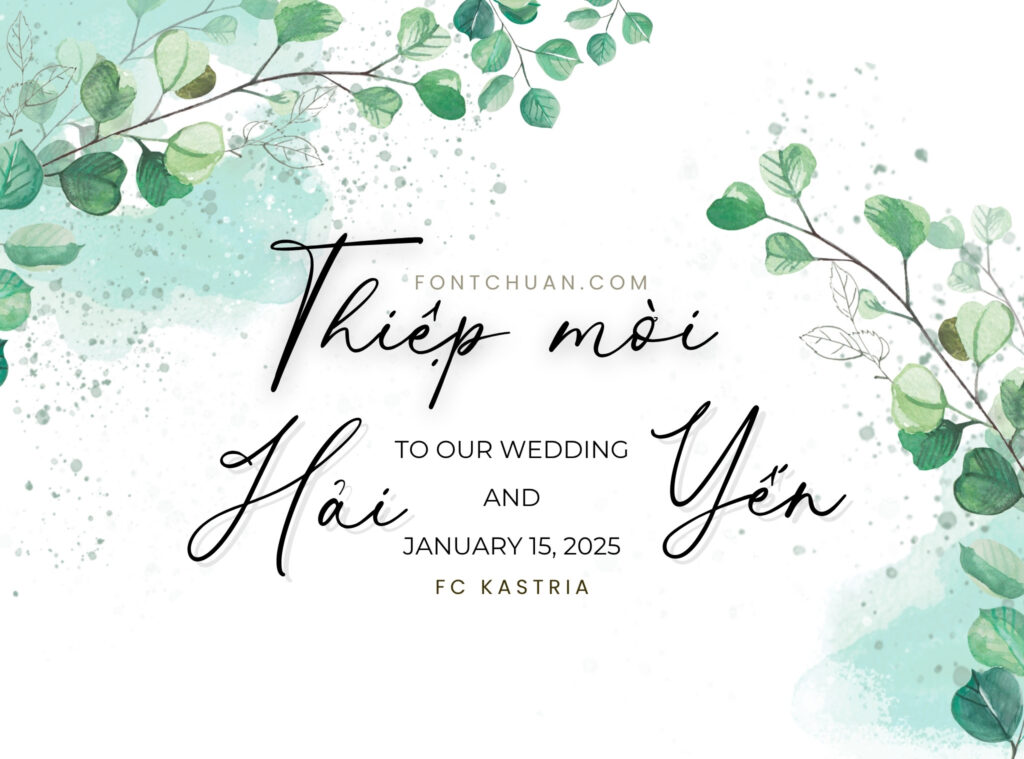
Font FC Kastria Việt Hóa
Kastria là một kiểu chữ ký tay vintage, được thiết kế bởi Muhamad Yusron Billah và phát hành bởi Creavibes Design. Font này mang đến sự thanh lịch và uyển chuyển, với các đường cong mềm mại, tạo nên vẻ đẹp tinh tế.
Về thiết kế, Kastria sở hữu các đường nét mượt mà, cấu trúc chữ phá cách và phong cách cổ điển tựa như Font chữ thư pháp, phù hợp cho nhiều mục đích sử dụng như ứng dụng cho ngành làm đẹp, thẩm mỹ, Spa, thiệp mời dịp cưới, truyền thông xã hội và các ấn phẩm quảng cáo khác.